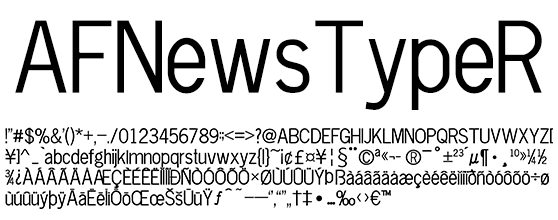
ニュースタイプ AFNewsTypeR
AFNewsTypeR
ニュースタイプは、定款や奥付け注意書きなど小さなエリアに配置する文章用の1バイトサンセリフ欧文フォントです。ウエイトはレギュラーサイズ、左右を詰め1行あたりに収められる文字数を増やせるように最適化、日本の住所を欧文表記する場合の訓令式やヘボン式で扱う Ô や Ō の文字も収録しました。